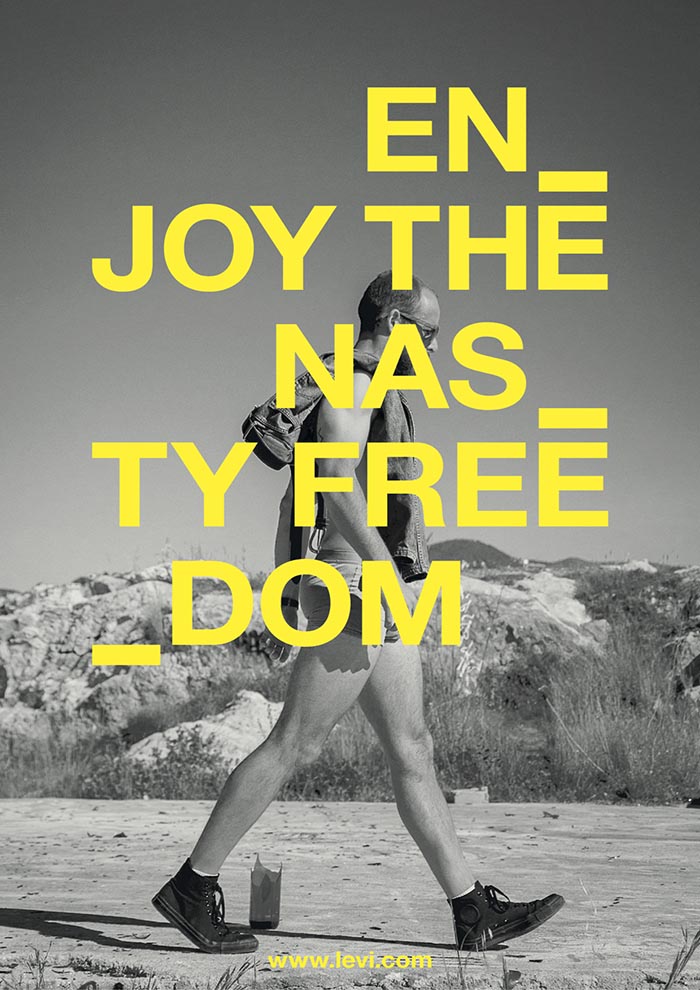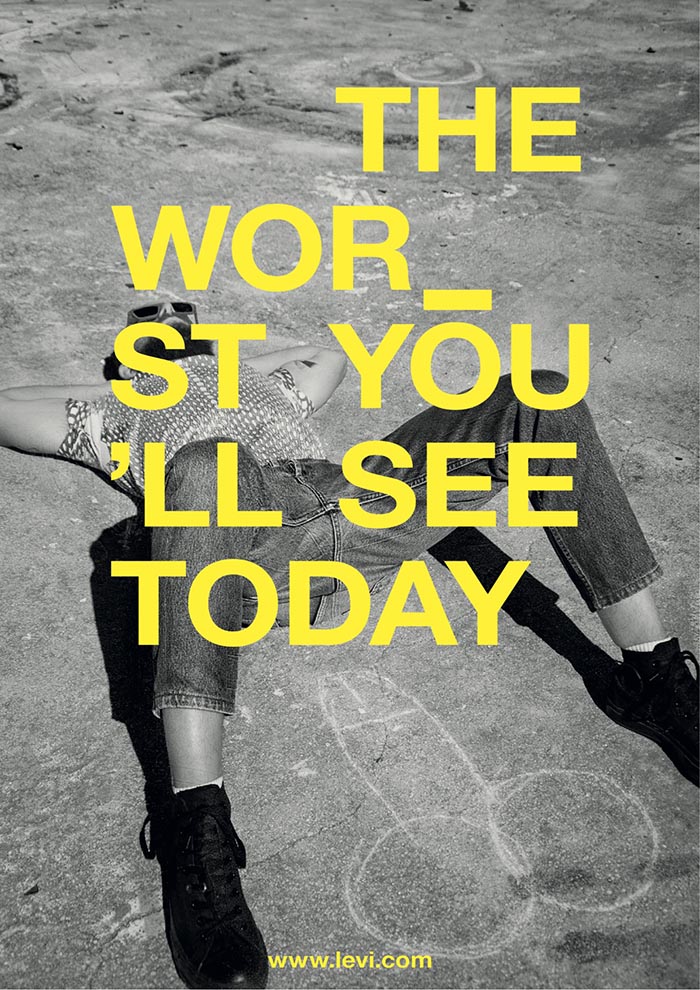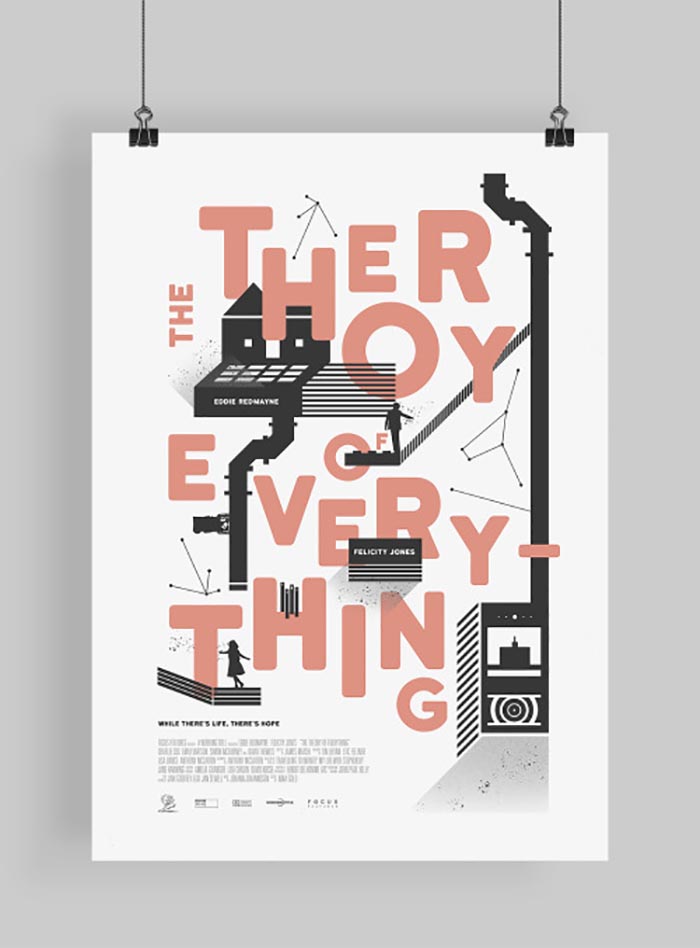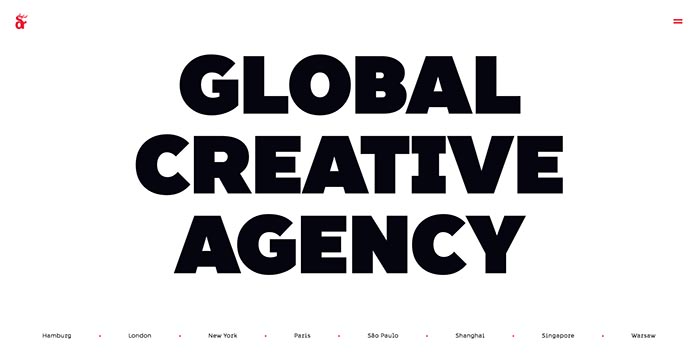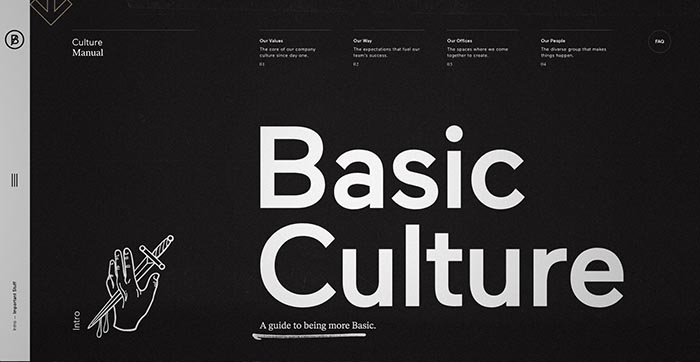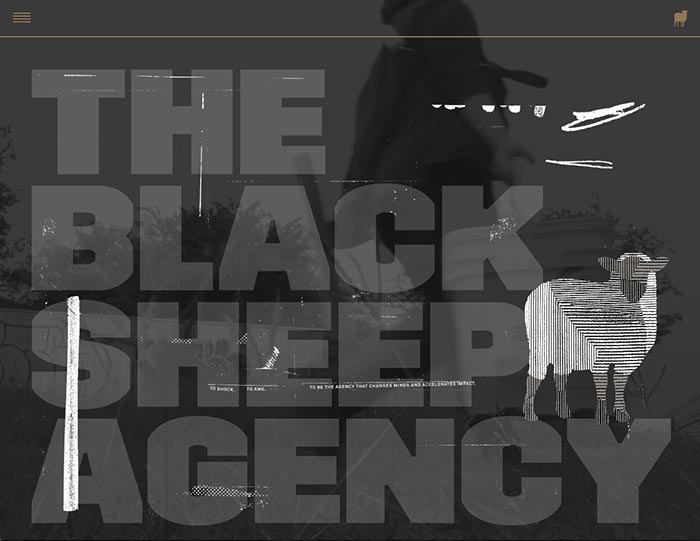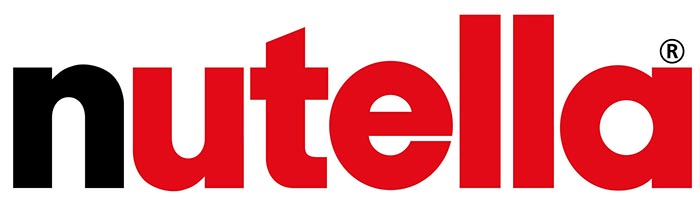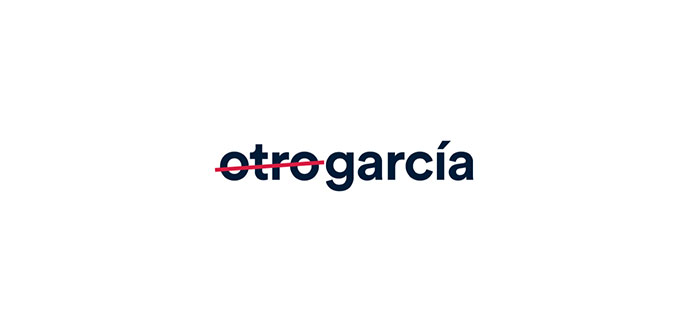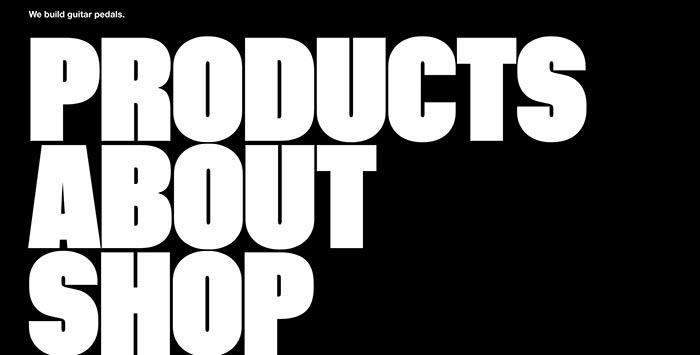
El tamaño sí importa: Tipografías bold
Ya te hablamos del flat design y seguimos con las tendencias en diseño gráfico con un poquito de tipografía rellenita y resultona, la tipografía bold. Porque aunque a algunos les escueza admitirlo, el tamaño sí importa.
Cartel tipográfico
No, no es un plato coreano, la bold es la negrita de toda la vida, pero a veces nos gusta darnos ese puntito de resabidillos y hablar en inglés.
La moda de la tipografía bold
Con el auge del lettering, la tipografía está pasando por una época dorada. Para tranquilidad de los que no somos ningún Iván Caiña ni otro grande del dibujo de letras, también hay sitio para nosotros, que trabajamos con letras prefabricadas.
La tendencia hacia un diseño más minimalista también le ha dado un buen empujoncito al renacer de la tipografía como centro de todas las miradas. En negrita, grande y dramática para impresionar. La letra domina diseños en logos, pósters, flyers y páginas webs.
Hablamos de diseños tipográficos donde la letra tiene todo el protagonismo y es imposible que pase desapercibida. Así, el resto de la composición, permanece clara y simple.
La tipografía cuanto más grande, mejor
Es una tendencia que le da personalidad a los textos que le quitan el protagonismo a la imagen y se convierten en el centro de atención.
Tipografía Avant Garde Gothic Bold
Si quieres que tu mensaje grite a los cuatro vientos, que tu logo no pase desapercibido, que tu web tenga personalidad o que tu póster sea visible de lejos, súbete al carro de las bold.
En diseño web, la bold es la reina
Página web – Frana FX
En diseño web, el texto es el que informa y posiciona, lo que le convierte en el elemento fundamental. Lo más importante es que sea legible y para ello, ¿qué mejor que una negrita grande? Tenemos que destacar los títulos con ellas y no olvidar que nada debería estar por debajo de los 16 px.
Si estás pensando en rediseñar tu web, no te lo pienses más. Déjate de llenar tu página con cosas que sólo distraen y vente con nosotros al lado oscuro, al lado de la tipografía grande y en negrita.
Página web – Basic Culture
Página web – Dragon Rouge
Página web – The Black Sheep Agency